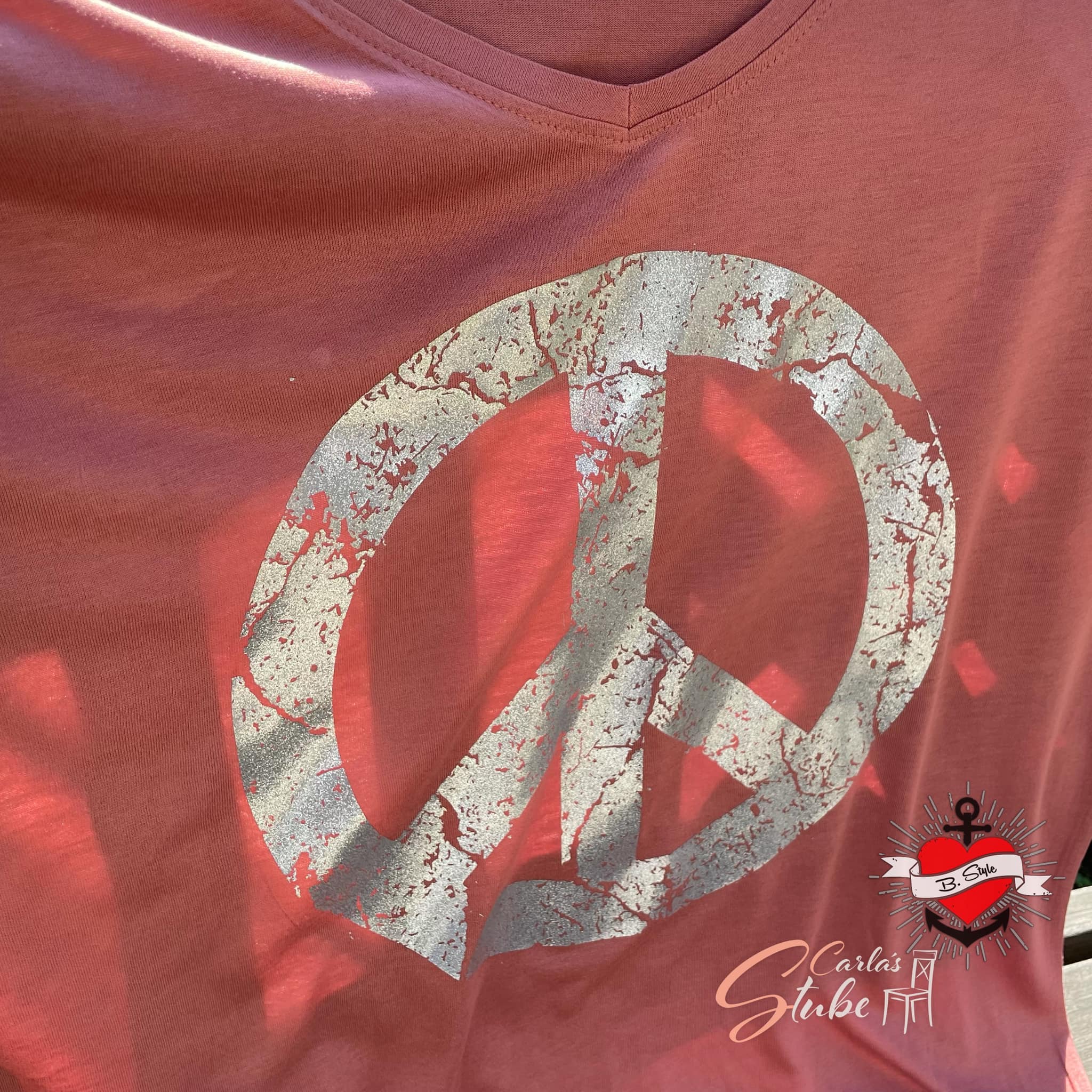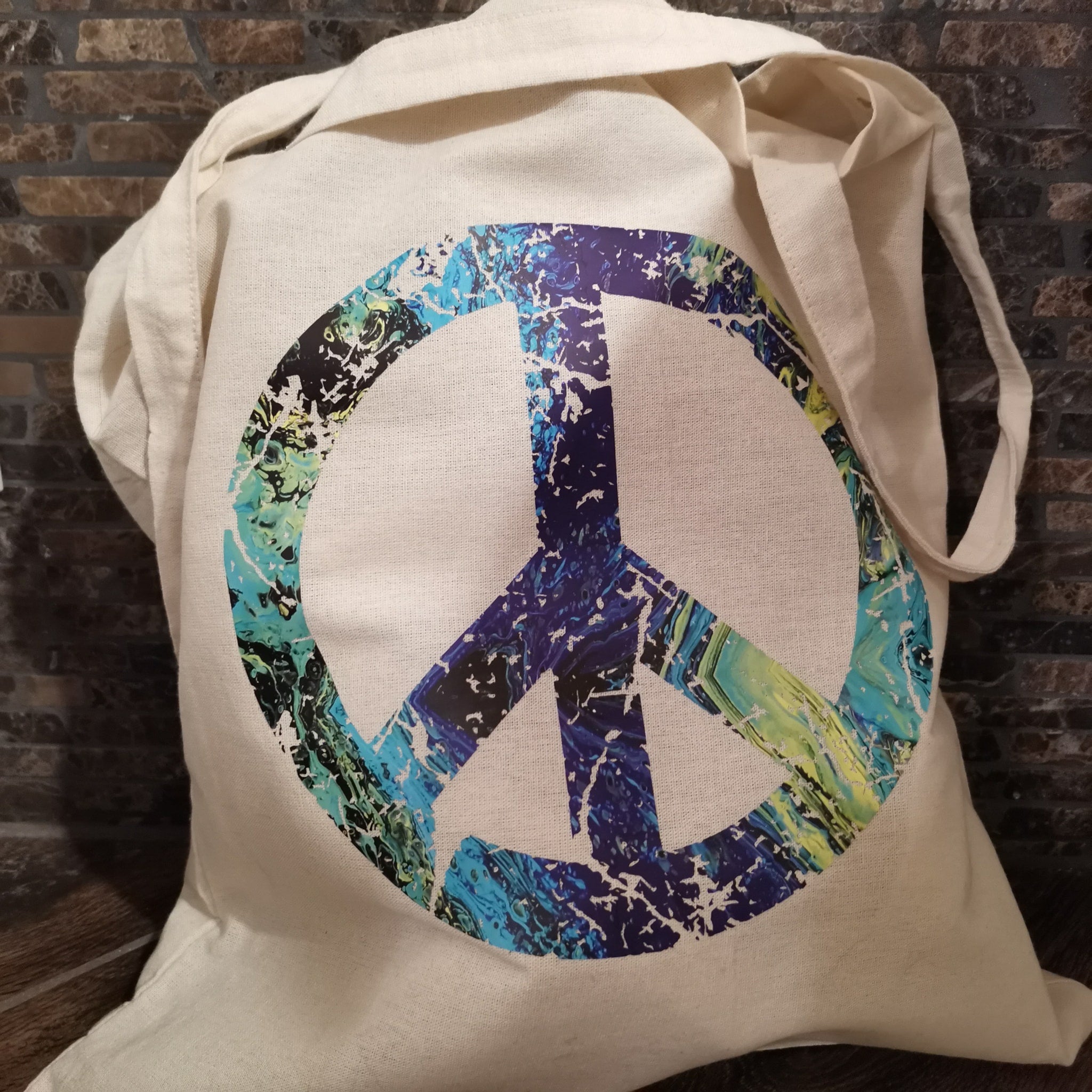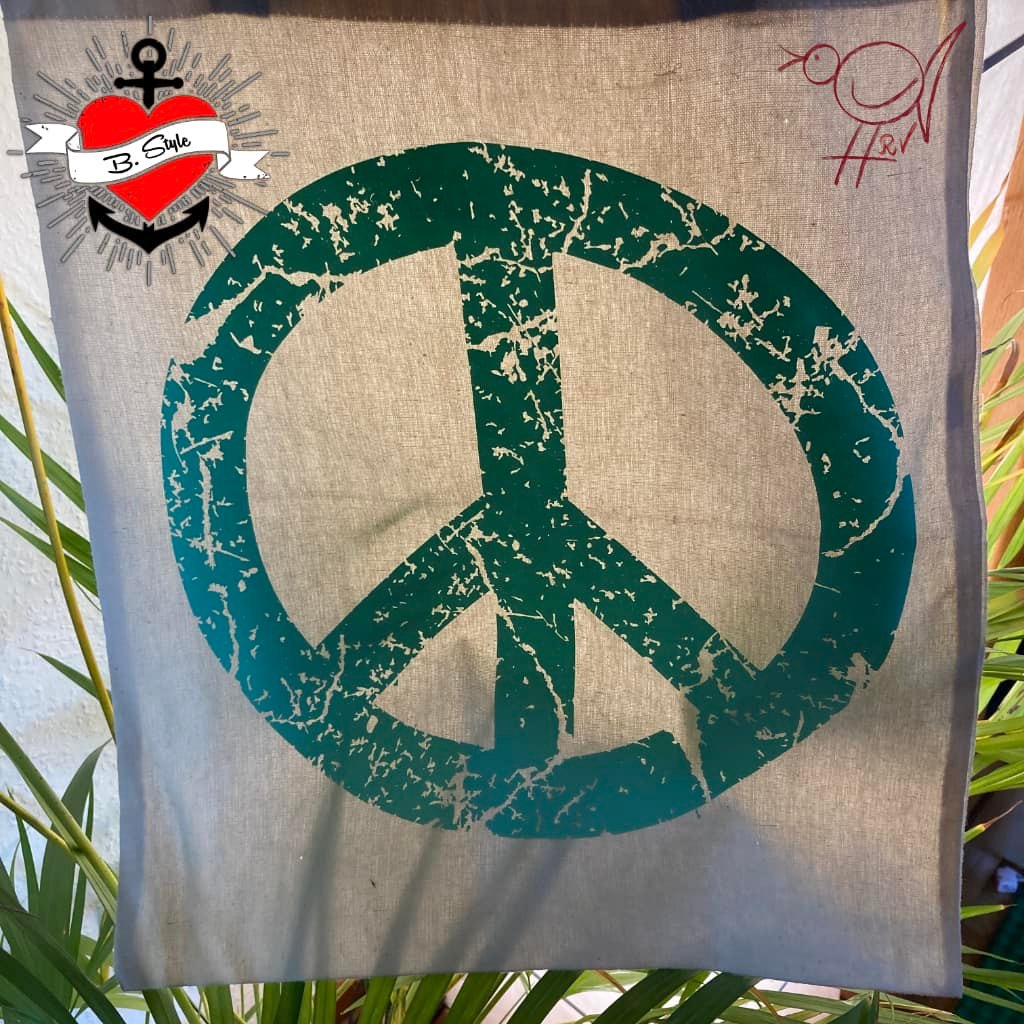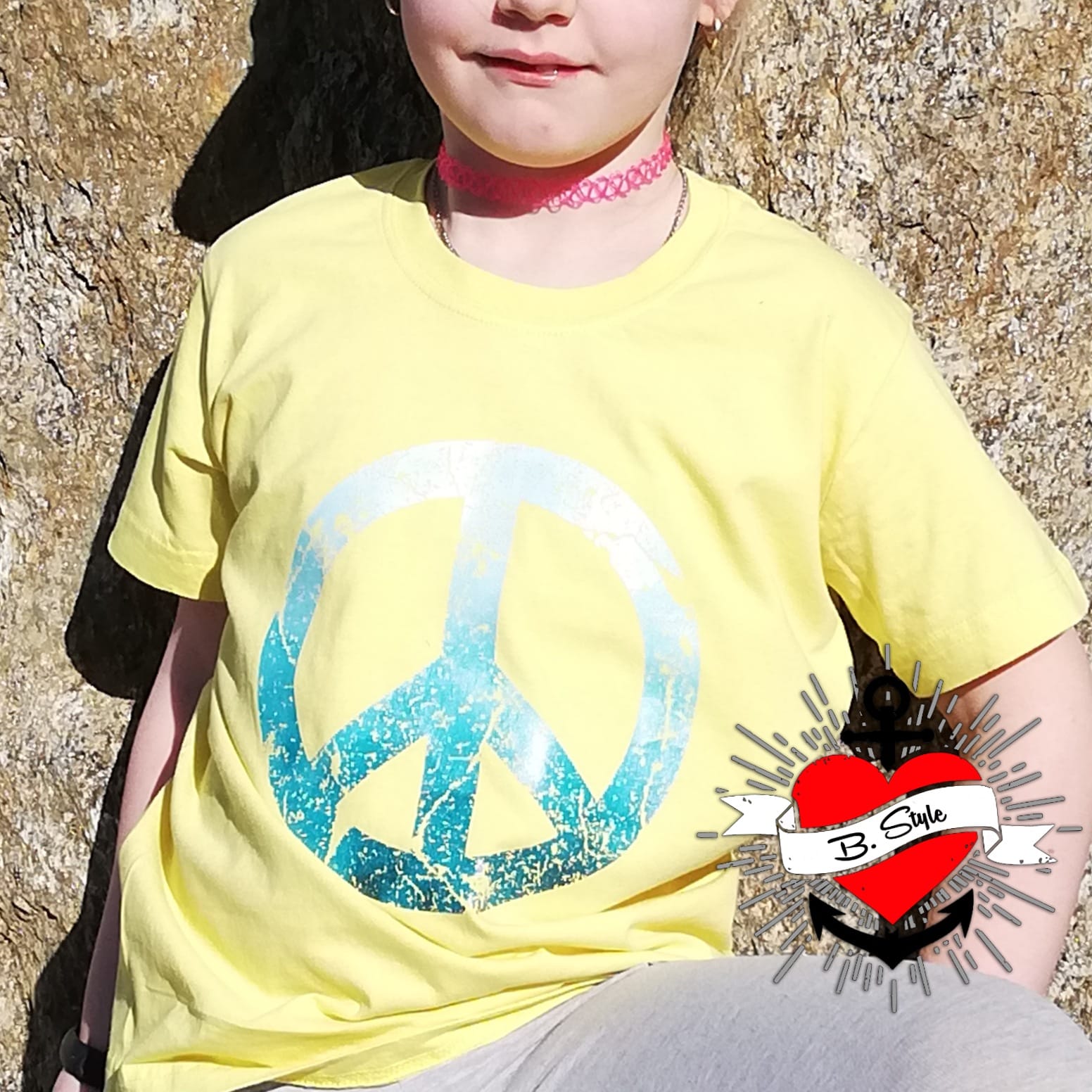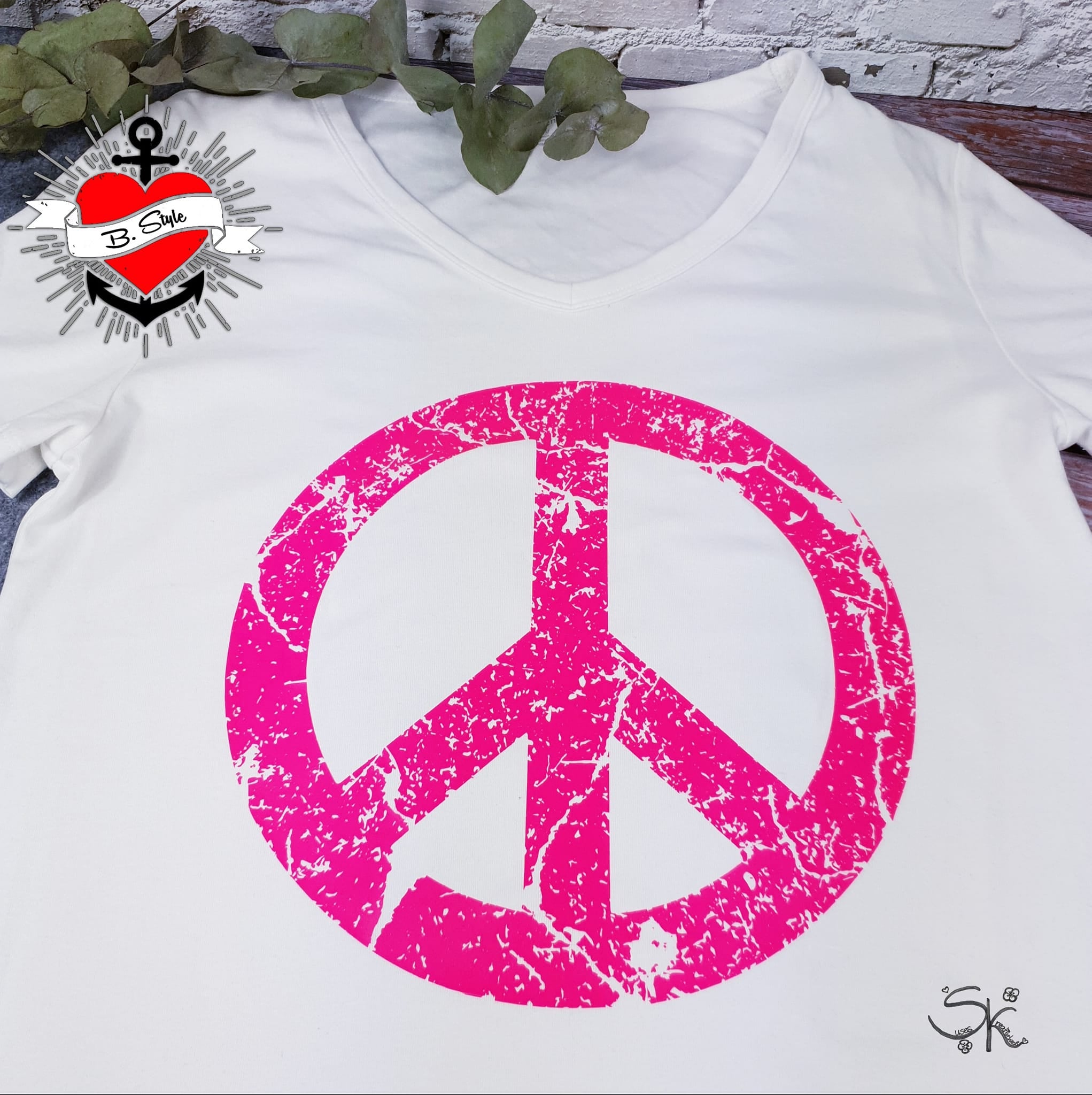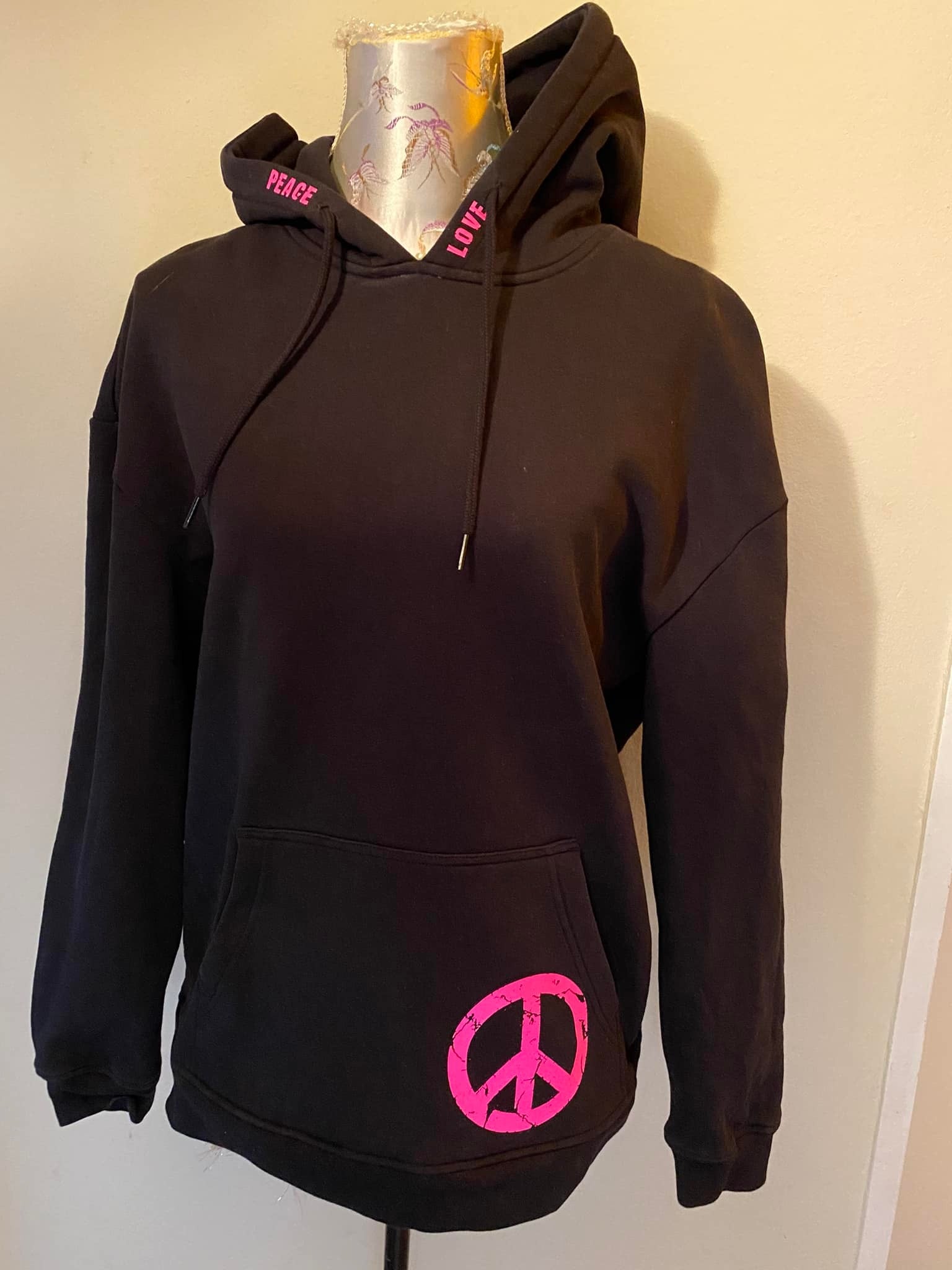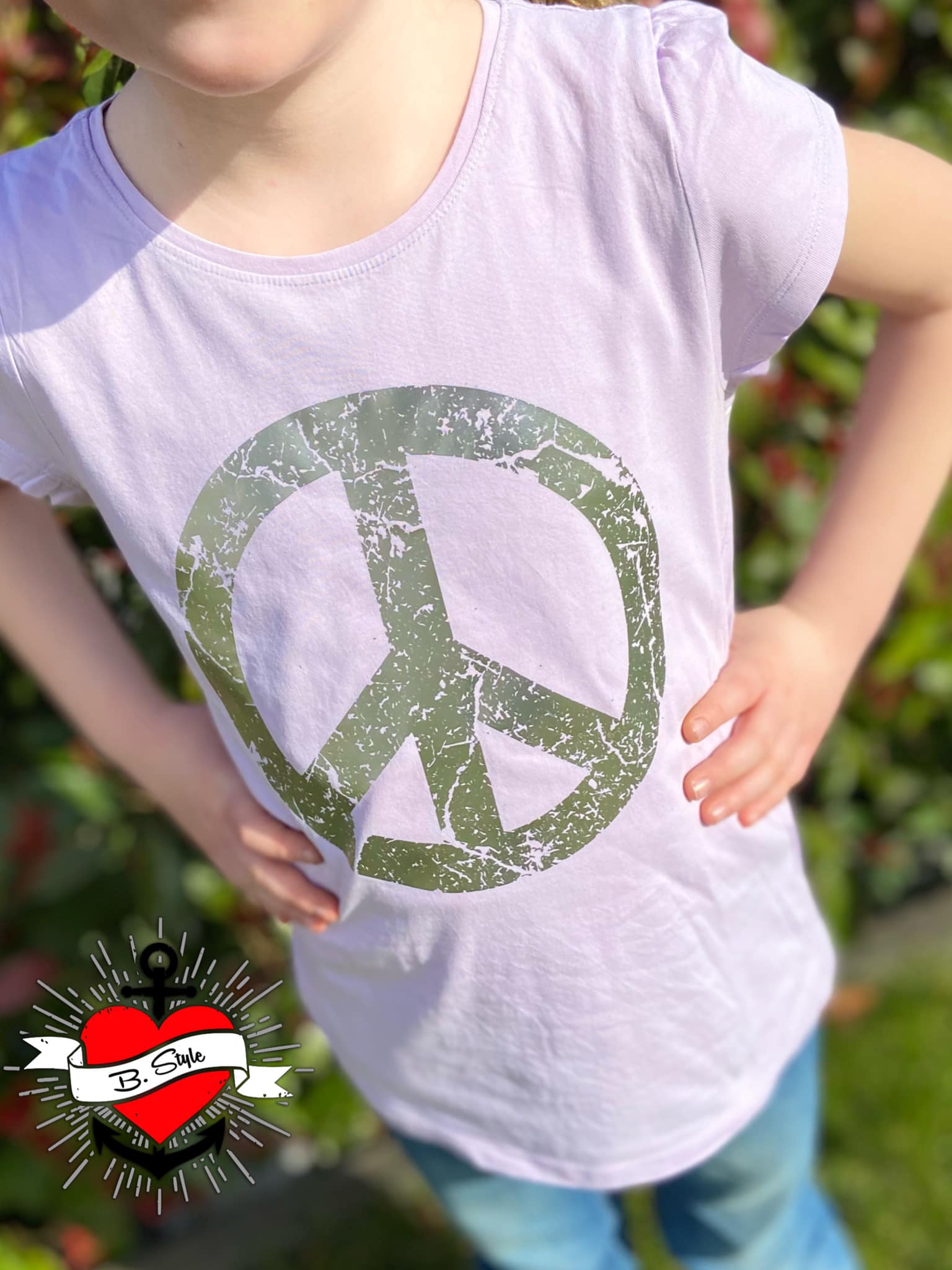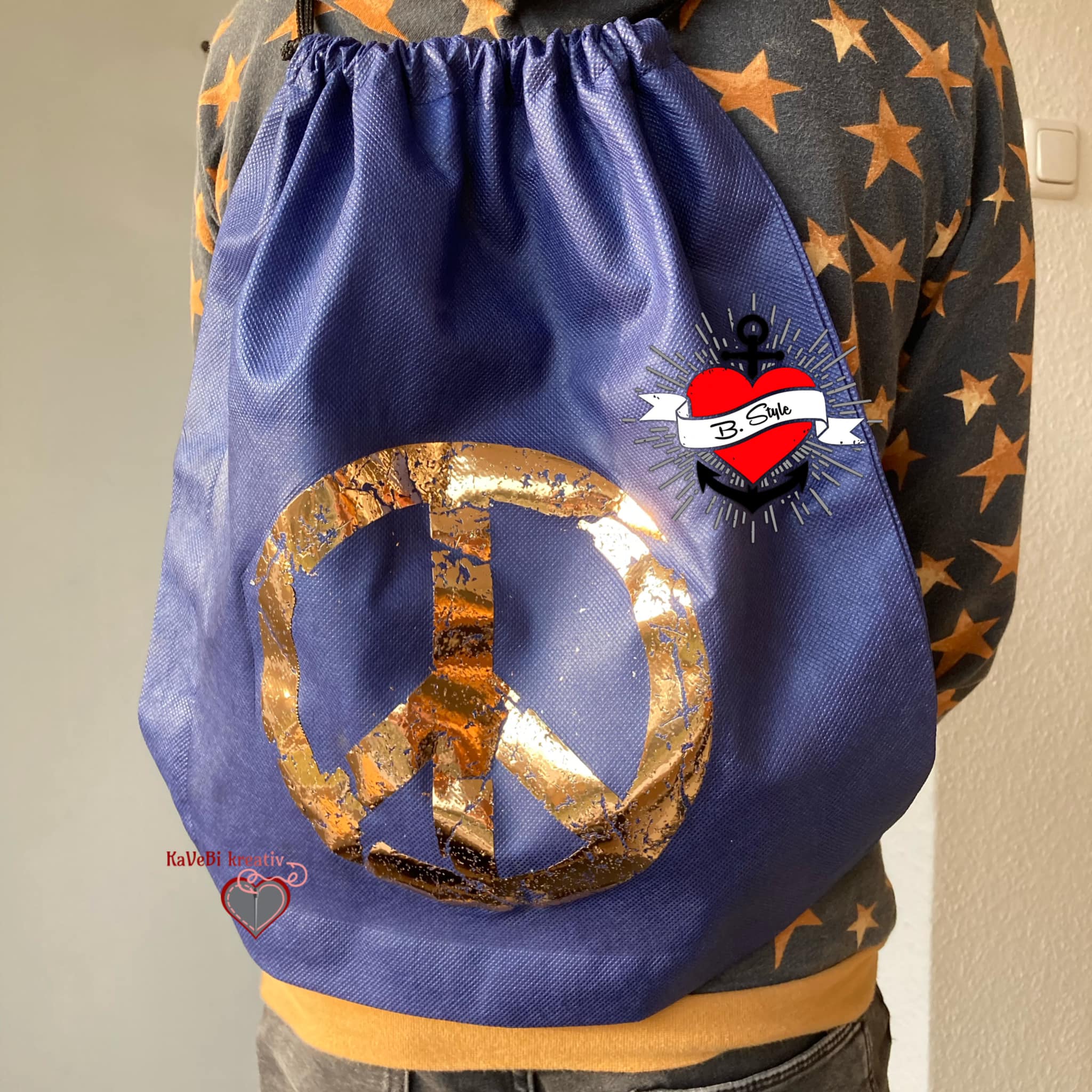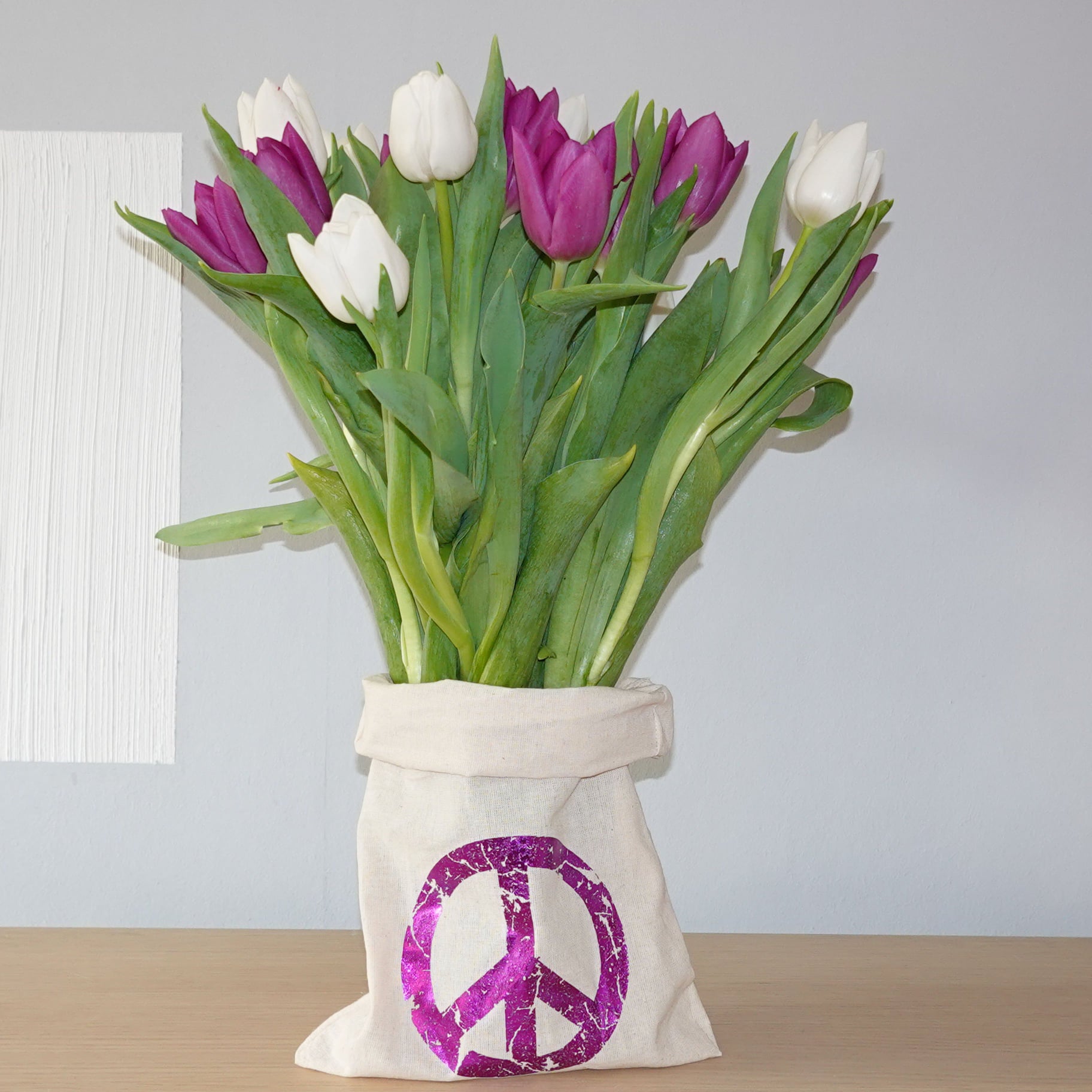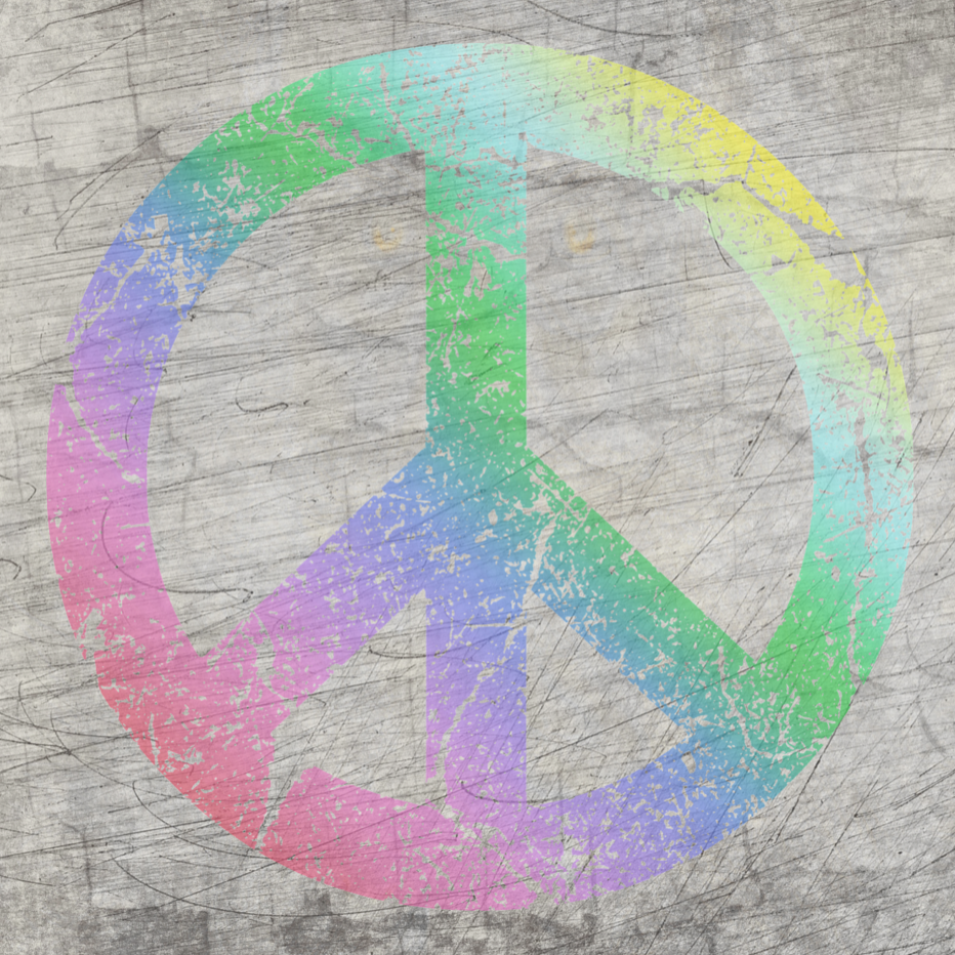
Plotterdatei - Peace
Entdecke die "PEACE" Grunge Schriftart Plotterdatei die speziell für kreative Projekte entwickelt wurde. Ob aus Holz, Acryl oder Materialien – mit dieser Datei kannst du deiner Kreativität freien Lauf lassen und einzigartige Produkte gestalten.